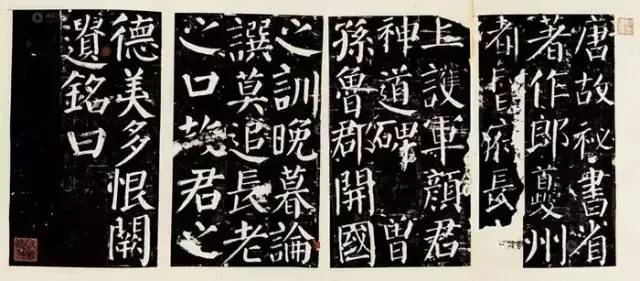
狼毫、羊毫和兼毫分别适合写哪种毛笔字体?
俗话说“工欲善其事、必先利其器”,写不同书体,自然要选择最适合的毛笔,毛笔选的不对,就要多费不少劲;毛笔选对了,就省事多了。下面书思给思友们聊聊“篆隶楷行草”五种字体的毛笔选择。
第一,写篆书,宜用兼毫毛笔。
篆书有大小篆之分,其书写的方法大致是一样的,主要是有其文字繁简的差别。大篆较繁,小篆较简,其书体的结构也就由茂密变得较为疏朗。结体上,大篆接近于甲骨文,结体错落有致,呈自然质朴之美。其用笔纯用中锋,用力匀平,流转自如。小篆的结构是以大篆演变而来,其结体较大篆更为工整齐律,呈匀称整饰之美。其用笔不但纯用中锋,而且笔势更为圆转流畅,显得朴茂端重。
篆书经数百年的演变,其字体虽有狭长、宽扁、尖削凝重之不同,但有共同的特征就是从不规则的形态而渐趋于规则的弧形圆写,从方峻的笔划变为匀称的线条,而习学篆字大都有相当笔龄,握笔相当稳健,因此可选用羊毫毛笔来书写,尤其长锋羊毫或长锋兼毫更能臻于至善境界。
第二,写隶书,宜用兼毫或羊毫。
隶书是将小篆的书体去其繁复、增减其体而创立。结体更为端正整齐,呈秀丽端庄之美。其用笔,如以汉隶为例,主要是横画的变化,蚕头雁尾,一波三折,尽情地舒展,呈委婉波状之势。如果说,篆书以弧笔著称,那么隶书则以波势见长。
隶书其字体仍存篆意,多逆笔突进,字体宽扁,波砾呈露。因此用笔必须宜于逆笔中锋书写,所以用羊毫毛笔或兼毫毛笔来书写较易表达。如果以狼毫毛笔书写,笔锋较健且尖,对于回锋、逆笔,必须更用心方能达到效果。
第三,写草书,宜用羊毫毛笔。
草书可分为章草、今草和狂草。而行草又因间于行书与今草之间,故一般又附于今草之中。章草是从汉隶演化而来的。章草的结体较为简约,其运笔既有草书的笔画,又有隶书的笔意,其主要特征是上下独立而不连写,字与字间也连接不多。
今草是从章草演进而来。结体也由章草的扁方趋于长方,但字与字之间仍少连接。其运笔加强了笔画与笔画之间的联系,并将带有隶意的章草捺笔完全去掉,显示出书法演变中形体和用笔方面的一大变化。狂草是草书中最为放纵的一种,其结体更为放逸奔放。运笔跌宕起伏,运转自如。字与字多连绵,即使笔与笔之间有时不连贯,但也显得笔断意连,一气呵成。
草书字体,在造形上颇有自由感,每一点每一划都具有节奏。所产生的美感与趣味必须轻松流畅。所以书写草书者,都具有多年笔龄,不限制选用笔性,颇能随心所欲,然而为求效果甚佳,皆以羊毫毛笔为主或是使用以柔性毛料制成的兼毫笔,因为笔锋选羊毫为主材料,笔腹笔腰配备较刚之狼毛、牛耳等其它加健物,作为支撑助力,可使笔毫柔顺流畅,笔力足,不枯涩,挥毫之下左右逢源。
第四,写楷书,宜用羊毫毛笔或兼毫毛笔。写小楷,宜用狼毫毛笔。
楷书是为规范草书的漫无准则和减省汉隶的波磔而由隶书的发展而逐渐演变而成的。楷书的结体呈平稳方正、典雅端庄。其用笔归之于“永字八法”,即点、横、竖、撇、捺、挑、钩和转折八法,十分强调用笔的笔力、笔势和笔意,讲究相互之间的长短结合、曲直并举、刚柔相济的艺术效果。
楷书一般来说是静态的书体,运笔速度较缓慢,注重笔压的加力,因此必须选用笔锋尖齐,笔腰较强健的毛笔,所以以狼毫和羊毫制成的兼毫笔为主,兼毫笔之笔锋柔畅,笔腰有力富弹性,在于点划、转折方面,容易收放。纯羊毫毛笔的笔性较柔,除特别嘉好者,甚少人用来写楷书,欲用纯羊毫毛笔写楷书,必须功力足,运笔认真,才能达成效果。
临摹各家字体亦需选笔,写柳体字,最好用狼毫毛笔,其次用兼毫毛笔,欧体字用笔亦以狼毫毛笔、兼毫毛笔较适宜,若选用笔锋笔颈部位较细直的更易发挥字韵。颜体字大都藏锋圆浑、厚重,以兼毫笔较宜表现,如使用狼毫笔则必须选笔锋、笔项较丰盈饱满者,只要轻按即可,若以细直的笔锋毛笔写颜体,必须加重用力,在落笔、转折、收笔之间,有深厚根基者方能达成,否则写出的字往往枯涩单调,无法显露颜体之美。
第五,写行书,宜用羊毫毛笔。
有人以为行书是从楷书中衍生而来。其实不然。行书和章草都是在正楷创立之前就已发明了,是与楷书并行不悖的书法。行书的结体介于楷草之间,近楷者则称“行楷”‘近草者则称“行草”。而楷书的每一种类型在行书中都有对应的形式。行书用笔比楷书活泼,而又没有草书的放纵,运笔生动灵活而富有生气。
行书的运笔速度较快,有缓急的变化,笔划的抑扬变化较多,笔顺也稍改变,而笔划由一笔进入另一笔时,往往以线连贯,仅具脉络,而不清楚分界线。为了把握住字体的气韵、高雅,除书家的用心外,选用的毛笔以狼毫、兼毫毛笔较适宜,因其较易把握住顿、挫、停、收、放。如使用兼毫毛笔,则以混合狼毛及其它加健物所制者,亦相当好用,但所表达风味不同,文字的优美较柔畅、圆润。
纯羊毫毛笔在书写行时,往往不易控制,非有深厚功力者很少尝试,若深知笔性,运笔速度快,喜好多项变化,增加浮沉或抑扬者,以纯羊毫毛笔来写行书可谓顺畅流利,另有一番风味。
所谓的书者不择笔,就是无论写哪种书体,用什么毛笔都可以。书法大师写隶书时,就用过羊毫毛笔和狼毫毛笔,也用过兼毫毛笔,而且写的都很好。
所以说,什么事情都没绝对的。对于初学书法者来说,可择笔。对于有一定功底的书写者来,用哪种毛笔都可以。
兼毫毛笔不但可以写篆书和隶书,还可以写草书和行书,若不信,可试之。